艺术字体图片是一种人为设计的机器视觉,所谓机器视觉便是以应用场景为设计的目标背景,有诸多设计者认为该种字体图片蕴含着大量的数字信息,而设计者的灵感则来自于各类图片和视频,将其进行转化后以艺术字的形式存在,正如字体视界中的许多艺术字体便是如此,那么为什么艺术字体图片被广泛使用呢,它有哪些优势呢?
艺术字体图片设计可以分成两部分,一个是商业化的,第二个是个人化的,商业化也就是我们平常的一些设计业务,商业设计我们需要注意什么?要注意这个产品的特质、品牌的含义、客户的喜好等,这些元素是需要考虑的,因为它毕竟用作商用,所以各个方面都需要兼顾。
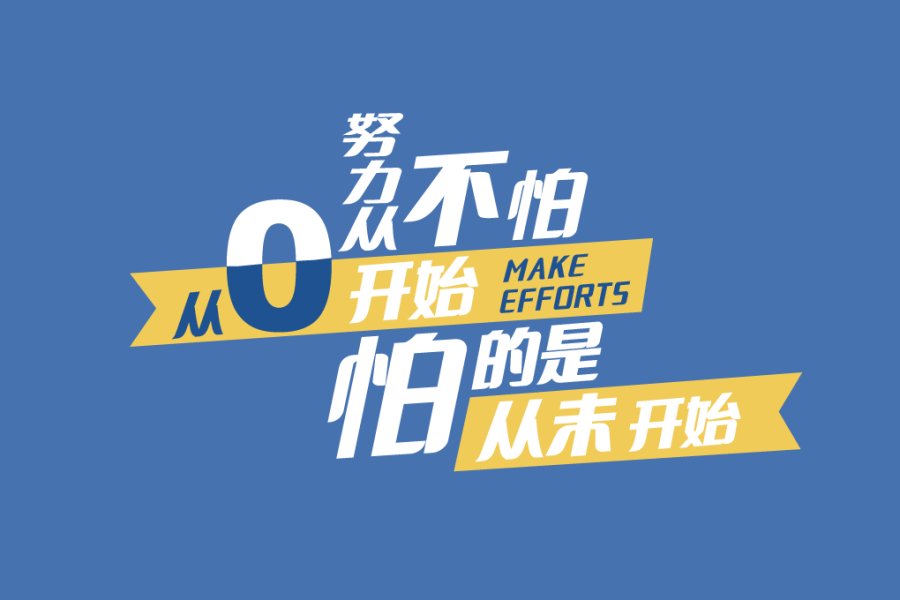
而个人的就相对来说比较简单,可设计一个能够表现自我情绪的字体,只需要把你想要表达的东西放在艺术字里面就可以了,是一种情绪的释放,去表达你的情感,这是一个非常舒适、非常享受的过程,可以在网上看到很多个人化的艺术字表达,这种艺术字通过大量的练习,积累一些方法和经验,再做商业主题时就会把握的更加恰当,更加准确一些。
平常的一些设计练习和商业设计也有关联,简单看一下logo艺术字体图片里边,也可以从前往后阅读一下,(大多数)应该有两个(及以上)不同的元素符号在内,如第1个是音符,第2个是义符,我们通过符号就能够非常明了的辨别出它是关于哪个领域和行业的艺术字。
总体来说艺术字体图片的有效分析利用是为商家增益的重要手段,而且随着制作技术的不断发展,该种机器视觉艺术延伸到各个领域,未来将会投身到不同行业,有着极大的文字艺术潜力。